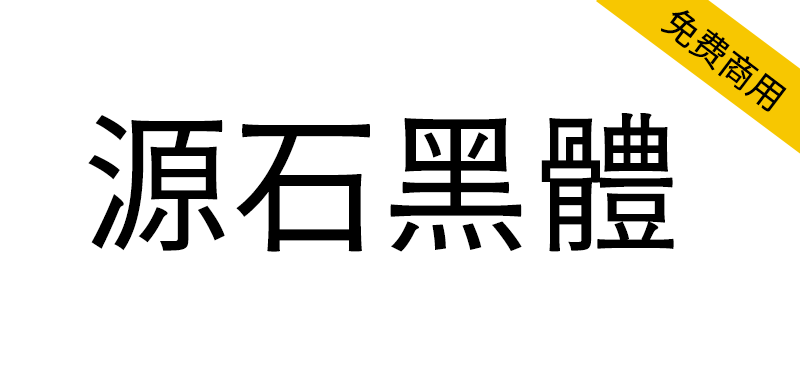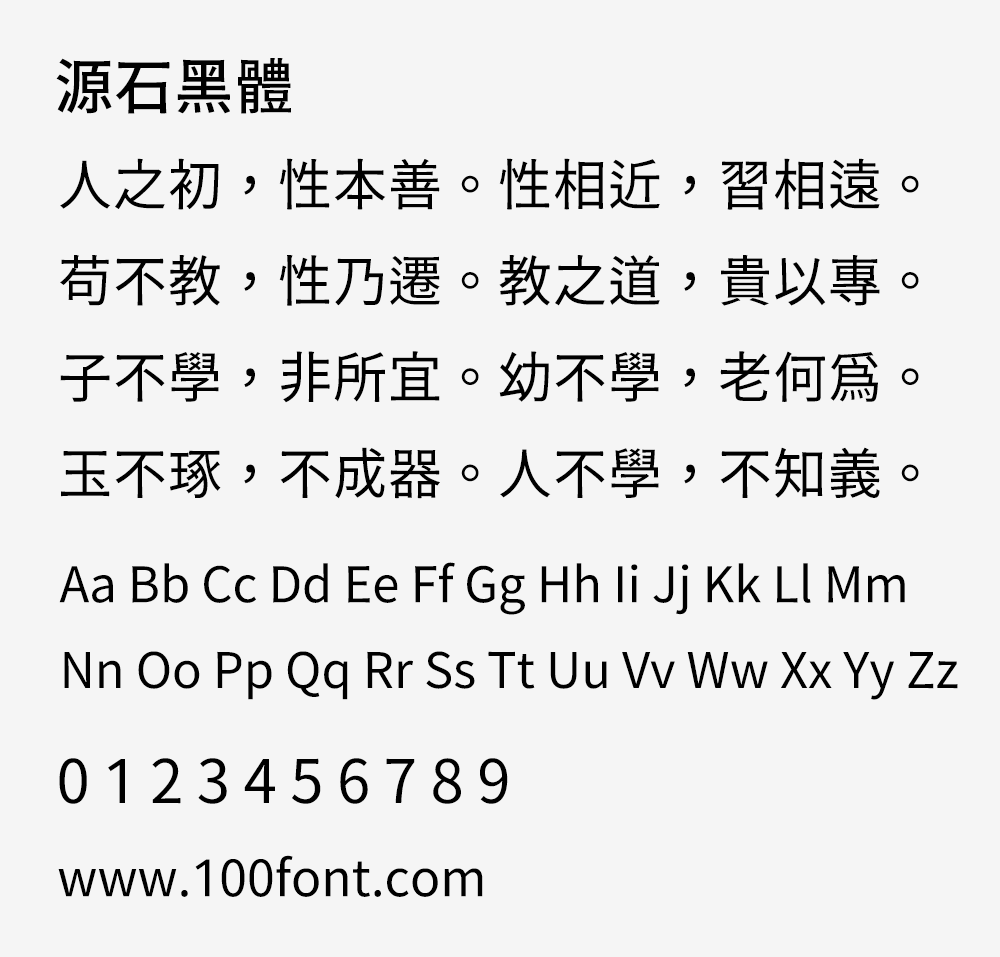
源石黑体是基于思源黑体的开放原始码中文字体。数位时代流行的黑体多数都是强调UD、粗细一致而锐利的风格。本字体则尝试重现早期年代较复古的黑体风格,较有温暖的气息。
免责事项:本字体乃以计算机程序自动进行改造,由于此风格造型有部分笔画难以猜测(例如是撇还是挑),部份文字可能有笔画误判的情形。由于此为兴趣性的开源字体项目,虽以试图强化猜测算法减少误判,但仍无法保证没有错误。在正式场合使用时请自行确认文字正确性。
注意提醒:这款字体主要适用于繁体,虽然简体中文、日语、韩语也支持,但是可能会出现错别字。